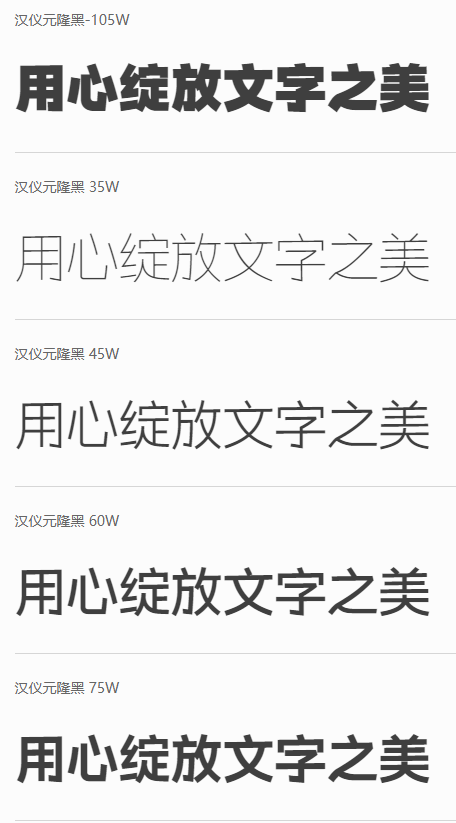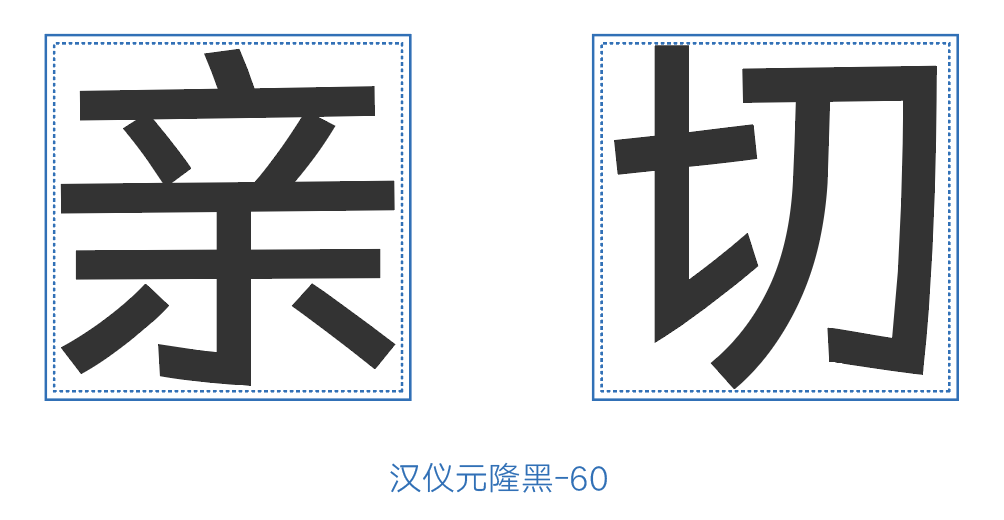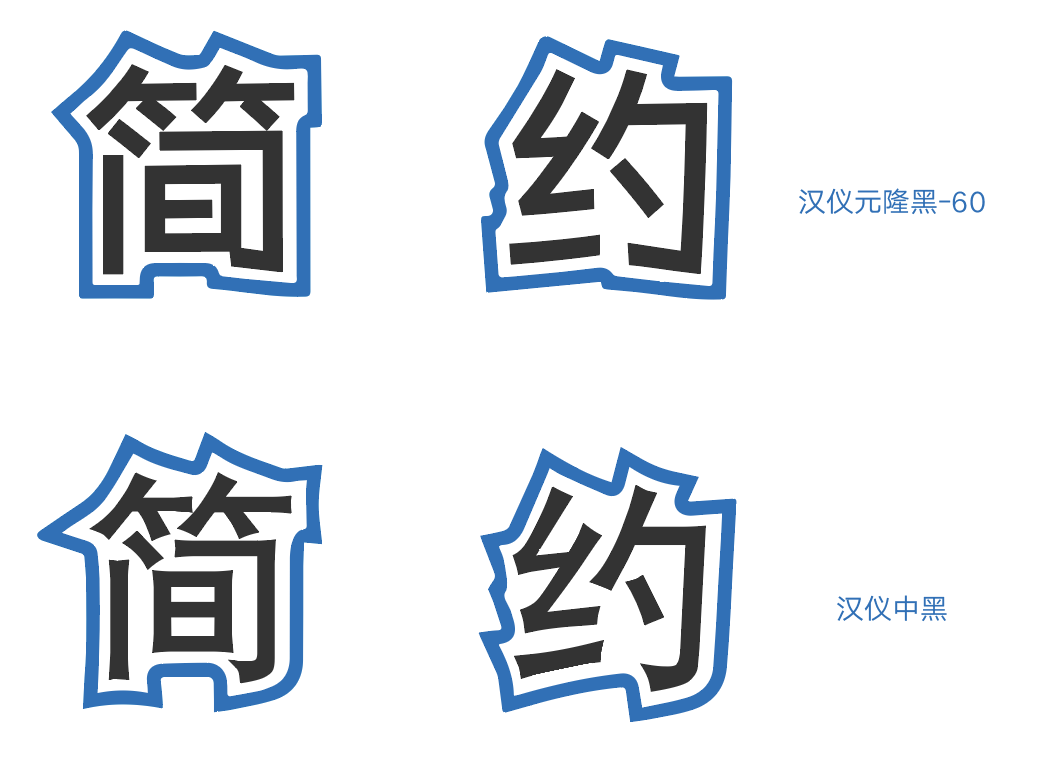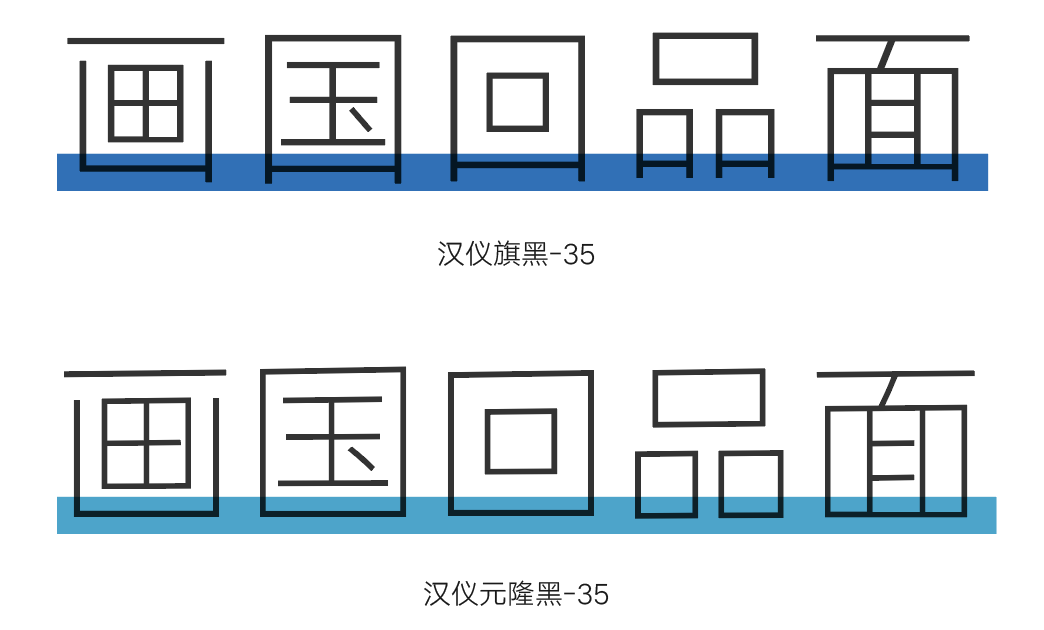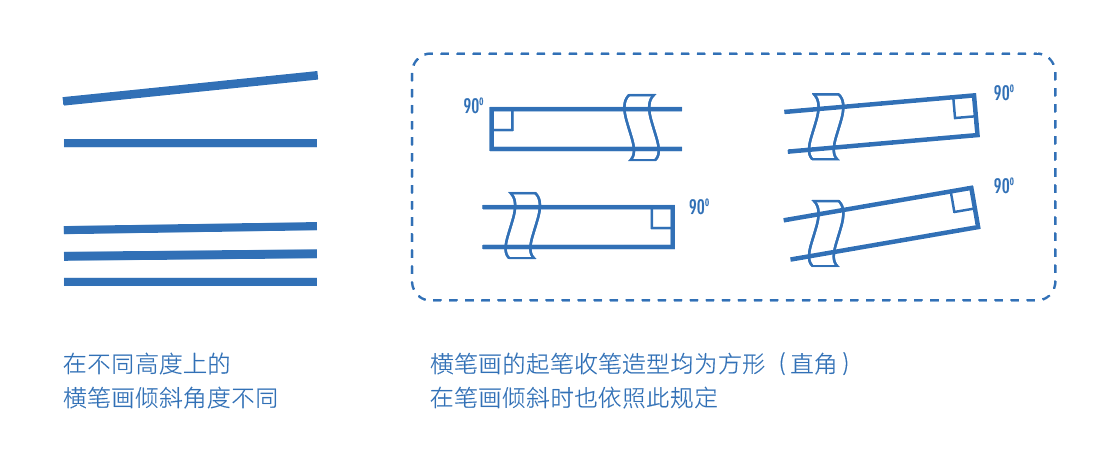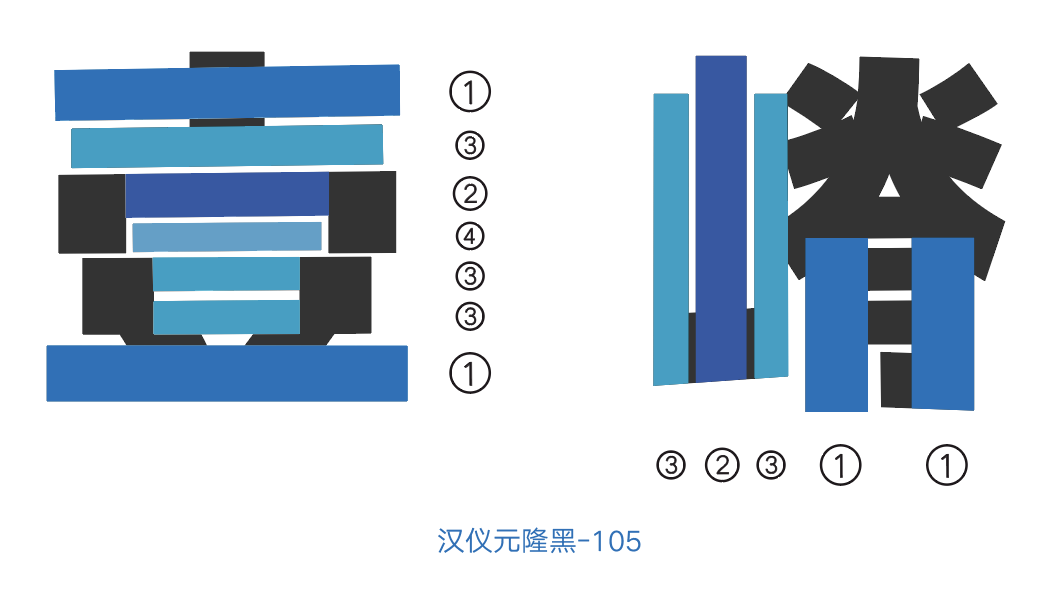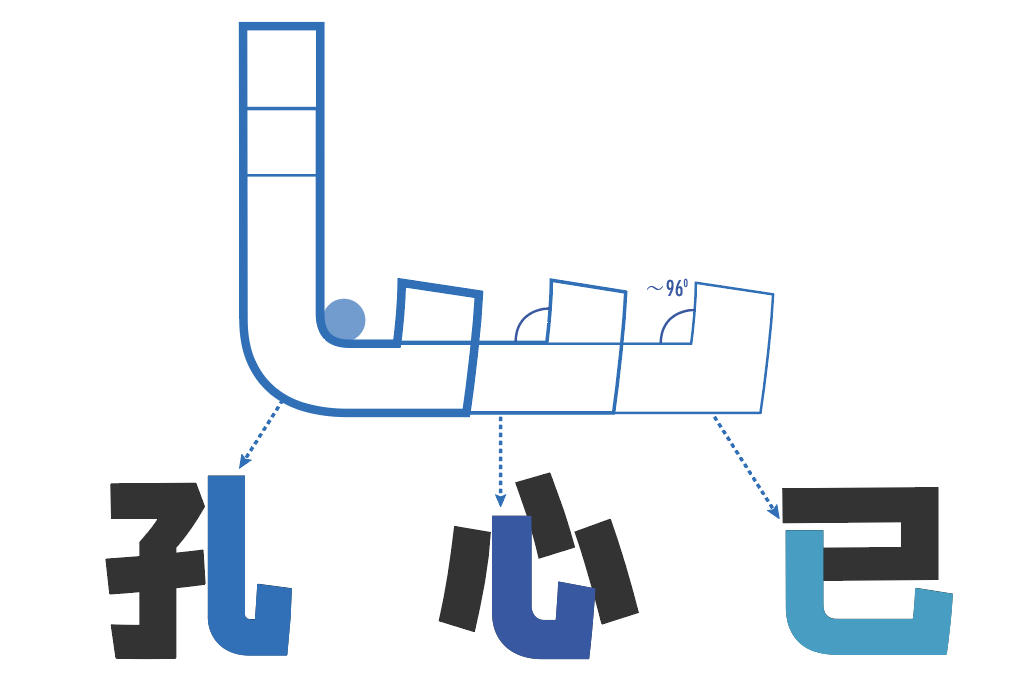
汉仪元隆黑家族系列
汉仪元隆黑家族 | 为版面而生的手写气质黑体
汉仪元隆黑是首届字体之星大赛的冠军,曾荣获过台湾金点设计奖。它针对正文排版及阅读功能对黑体进行了全方位的优化,这款轻松舒适的黑体字在众多作品中脱颖而出,广受好评。它共包含6个字重:汉仪元隆黑-35/45/60/75/90/105,满足了不同版面的需求,为设计师提供了更多选择。
汉仪元隆黑家族 | 字形特点
汉仪元隆黑家族这款字体字形端正,笔画浑厚且饱满。它不同于一般黑体字严肃、庄重的特点,而是着力体现清新、自然、舒适、松弛、敦厚的特点,保留了手写汉字时自然右上倾斜的痕迹。
汉仪元隆黑家族的外形轮廓简练,多用直线或弧度较小的曲线来概括。
汉仪元隆黑家族的“口”结构底部没有出头,笔画无过多修饰,体现出元隆黑的简约与自然。
汉仪元隆黑家族 | 笔画特点
汉仪元隆黑家族的笔画有略微上挑的趋势。“横”笔画根据在字体结构中的不同位置及空间关系,形成不同的倾角,且角度从上而下依次减小。这是不同于其他黑体的细节和用心之处。
汉仪元隆黑家族里的粗体字(如汉仪元隆黑-105)根据不同笔画的位置和重要性,为了使字体结构得到更合理的展现,对不同位置的笔画进行了合理的布局,以达到整体灰度的平衡。
汉仪元隆黑家族的“竖弯”部分是固定而统一的,“钩”可随具体情况调整长短。
汉仪元隆黑家族的“竖钩”在保持笔画角度的基础上,通过调节“钩”部分的长短来满足不同空间的需求。
考虑到不同字重的布白效果,元隆黑家族的粗体(60/75/90/105)和细体(35、45)在转角的处理方式,粗体的折角方式又不同于端正严肃的旗黑,斜切的方式更符合书写的特性,也很好地诠释这款黑体家族的手写质感。
汉仪元隆黑家族 | 字重特点
汉仪元隆黑家族系列包含6个字重:汉仪元隆黑-35/45/60/75/90/105。因为元隆黑是家族字体,因此在字面比例不变的情况下,随着字重变大,字体的中宫会有变小的趋势。
相比汉仪元隆黑-35而言,由于汉仪元隆黑-105字体的加粗,使笔画的关系变得紧凑,聚拢。
家族字体不是简单的线性变化。汉仪元隆黑家族的粗体和细体分别进行了设计,用差值的方式实现了整个字体家族,从而满足设计师对不同视觉层级的表达需求。
汉仪元隆黑家族 | 功能特点
汉仪元隆黑-105/90/35适合放大字号,用做大字报、宣传语和海报等。汉仪元隆黑-75/60适合做标题用字,汉仪元隆黑-45的粗细设计适用于正文应用。
汉仪元隆黑家族 | 西文字母
汉仪元隆黑家族为了保持较好的可识别性和易读性,西文字母采用较高的x-height,非常适宜在较小字号下的正文使用。
汉仪元隆黑家族的西文字母同样有着自然、舒适、松弛、敦厚的字体感觉。相比旗黑家族,元隆黑家族的西文如“O”、“D”等曲线字母比较圆润,“M”笔画比较开阔,保留了手写字母的自然痕迹。